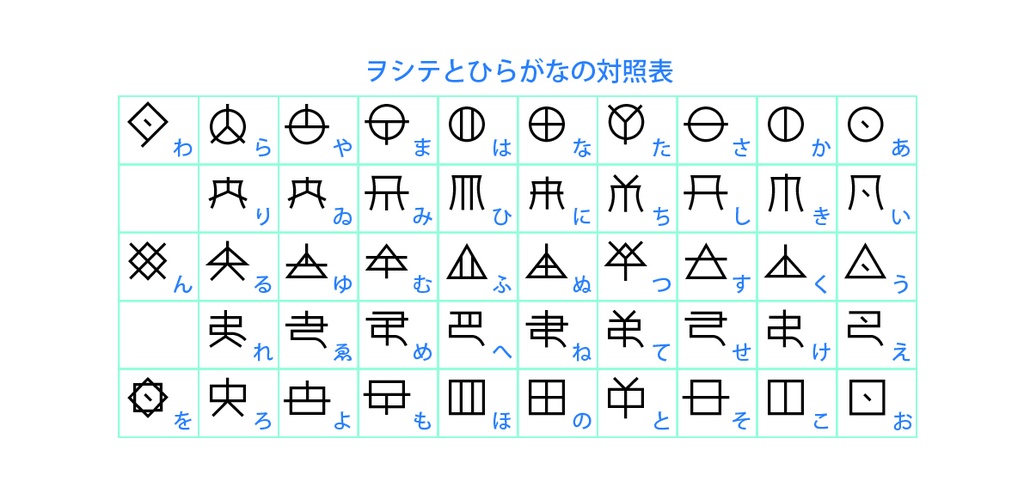
神代文字ヲシテ ゴシックRegularフォント
神代文字ヲシテのゴシック体フォントです。フォントのウェイト(太さ)はRegularです。 WindowsやMacで使用できるOpenTypeフォントです。 ヲシテとは古代の日本で使われていたといわれる神代文字のひとつ。旧来はホツマ文字とも呼ばれていました。「フトマニ」「ホツマツタヱ」「ミカサフミ」などの文献の記述に使われています。 48文字のヲシテがあるので、ひらがなを入力すると相当するヲシテが表示されるようにしました。 【収録文字】 ひらがな(あいうえおかきくけこさしすせそたちつてとなにぬねのはひふへほまみむめもやゆよらりるれろわゐゑをん) ※濁音、半濁音、拗音、促音はありません。 【データ内容・使用方法】 zipファイルを解凍してください。 OTFファイル pkwoshiteg1-Regular.otf JPGファイル(ヲシテとひらがなの対照表) font-sample.jpg テキストファイル readme.txt が収録されています。 pkwoshiteg1-Regular.otf をインストールしてください。 【購入の際の注意点】 商用利用OKです。 使用した場合、ご一報いただけるとうれしいです。Twitterなどで紹介します。 フォントファイルの改変・再配布は禁止です。 ※2025/1/19 「ゑ」の文字が「れ」と同じだったので修正しました。